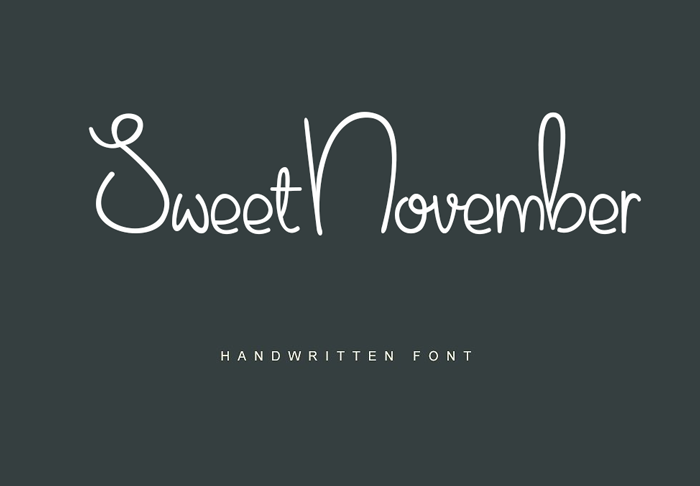
Sweet November Font – Download Grátis
Introduzimos Sweet November Font, uma elegante escolha para designers e criativos. Desenvolvida pelo designer Haidi Shabrina, esta fonte script moderna é perfeita tanto para projetos profissionais quanto para expressões artísticas. Cada letra foi cuidadosamente moldada para criar texturas harmoniosas que tornam o seu texto visualmente atraente. Com sua estética de letra moderna e sofisticada, Sweet November está ideal para uma variedade de propósitos, como citações, cabeçalhos de blogs, cartazes, casamentos, marcas, logotipos, moda e vestuário, cartas, convites, embalagens de papelaria, entre outros. Este é um excelente remendo para quem busca uma fonte que combine elegância com versatilidade em projetos digitais. Sweet November traz a essência da escrita à sua página ou projeto, oferecendo um toque único e sofisticado que certamente deixará seu design mais profissional e envolventemente bonito. Experimente Sweet November para dar vida aos seus projetos de design.